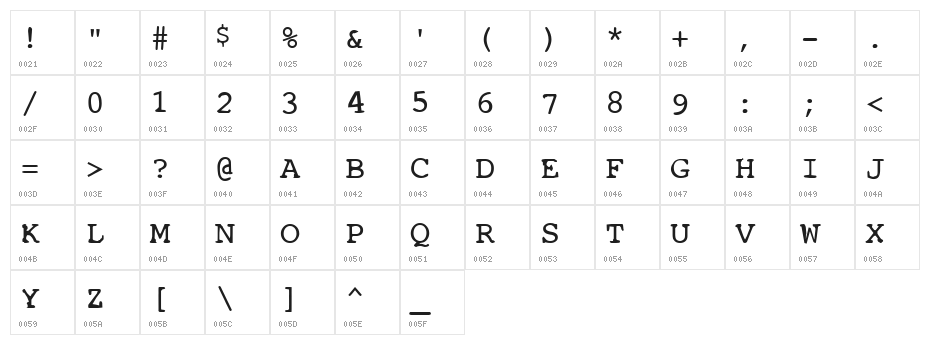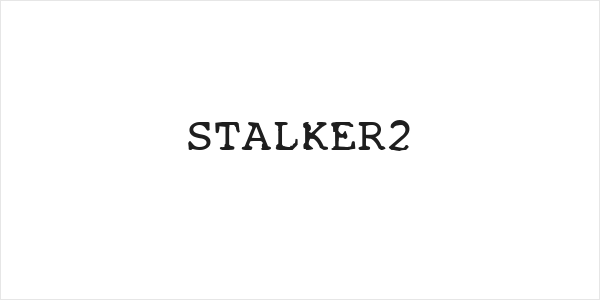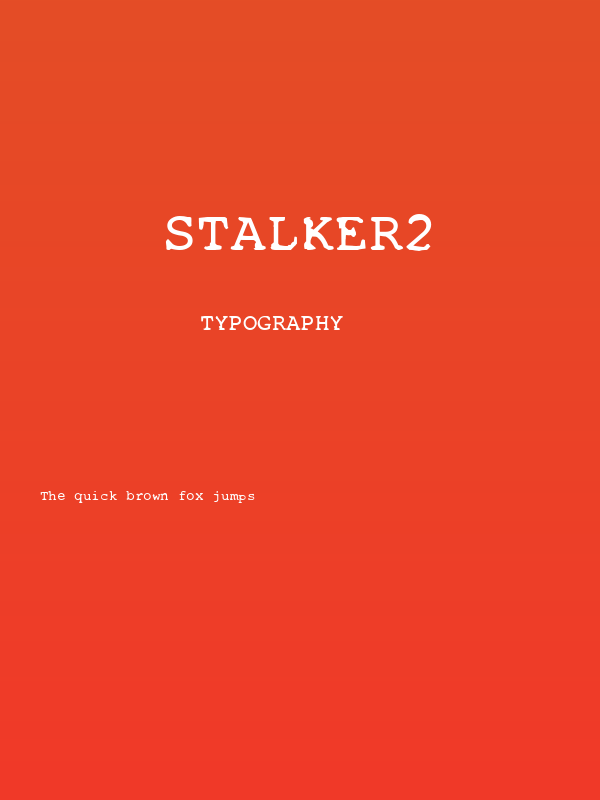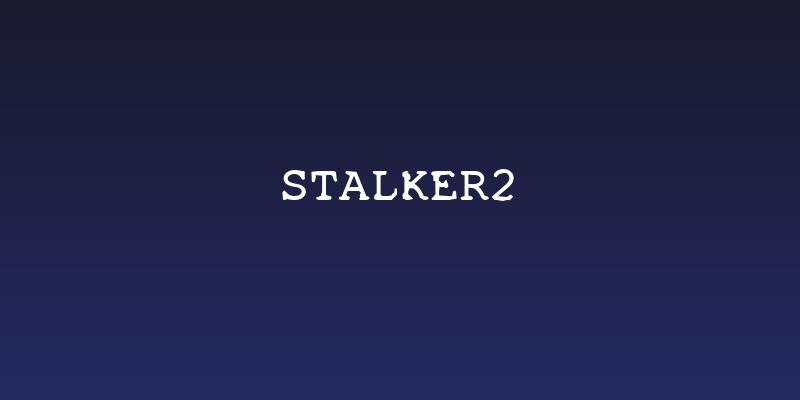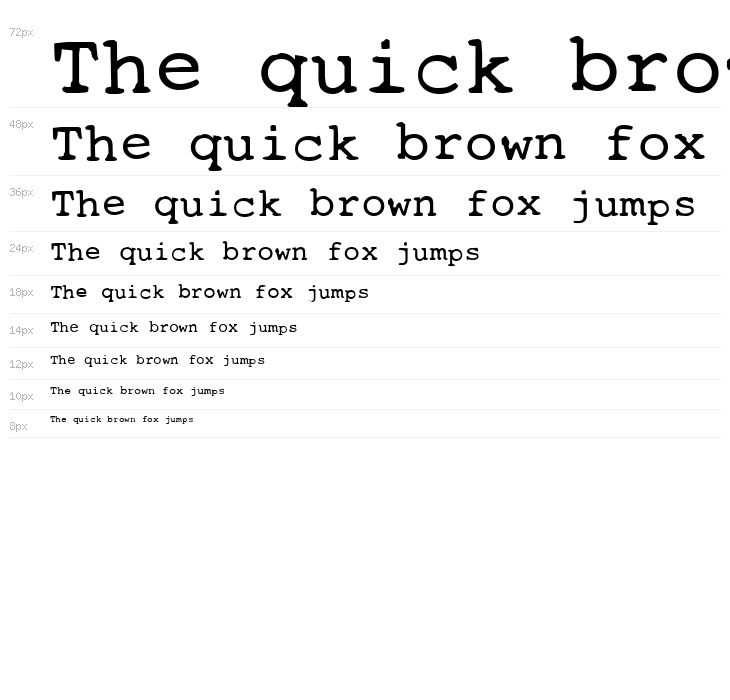
STALKER2 Font
✎ Typewriter
| Categorías | Typewriter |
| Estilo general | Vintage |
| Caso de uso | Headlines, Body text, Logos |
| Proyectos propuestos | Ideal for projects that require a retro or vintage aesthetic, such as posters, book covers, or digital media that aim to evoke nostalgia. It can also be used in coding environments or for creating documents that mimic typewritten text. |